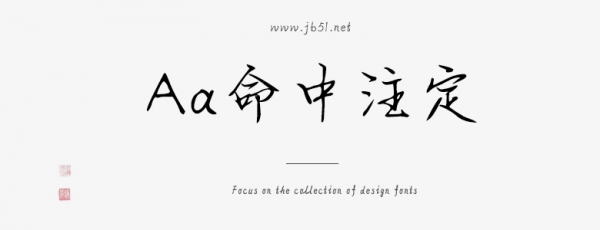
Aa命中注定 是一款不錯(cuò)的藝術(shù)字體,由Aa字庫(kù)出品,字體筆觸略細(xì),書寫流暢 ,具有很好的視覺感,適合應(yīng)用于藝術(shù)設(shè)計(jì)、平面宣傳設(shè)計(jì)、網(wǎng)頁(yè)設(shè)計(jì),書法字帖等領(lǐng)域,需要的朋友可以前來本站下載。